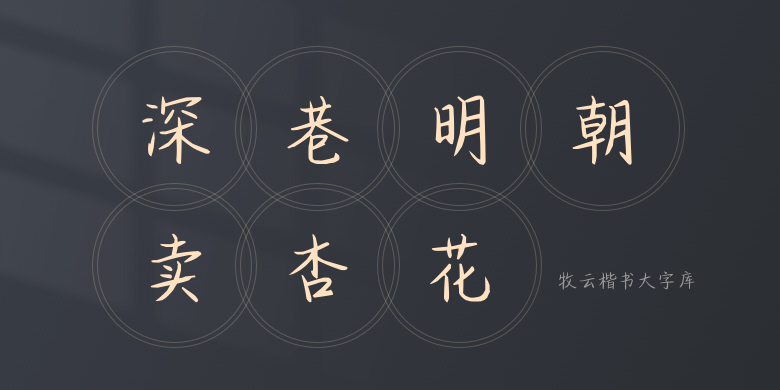
牧云楷书大字库
牧云楷书大字库,这款字体结构工整、笔画清晰,兼顾美观与易读性,适用于标题、正文、海报、包装、LOGO 等多种场景。字形优雅稳定,风格百搭耐看,适配日常排版与创意设计,让文字呈现更舒适、更具质感。牧云楷书大字库一笔一画,皆是细节,以均衡的比例、流畅的线条打造舒适视觉体验,字形端正大气,风格简约现代。无论是商业设计、品牌宣传还是日常排版,都能轻松驾驭,让文字更有格调与力量。牧云楷书大字库字体下载。